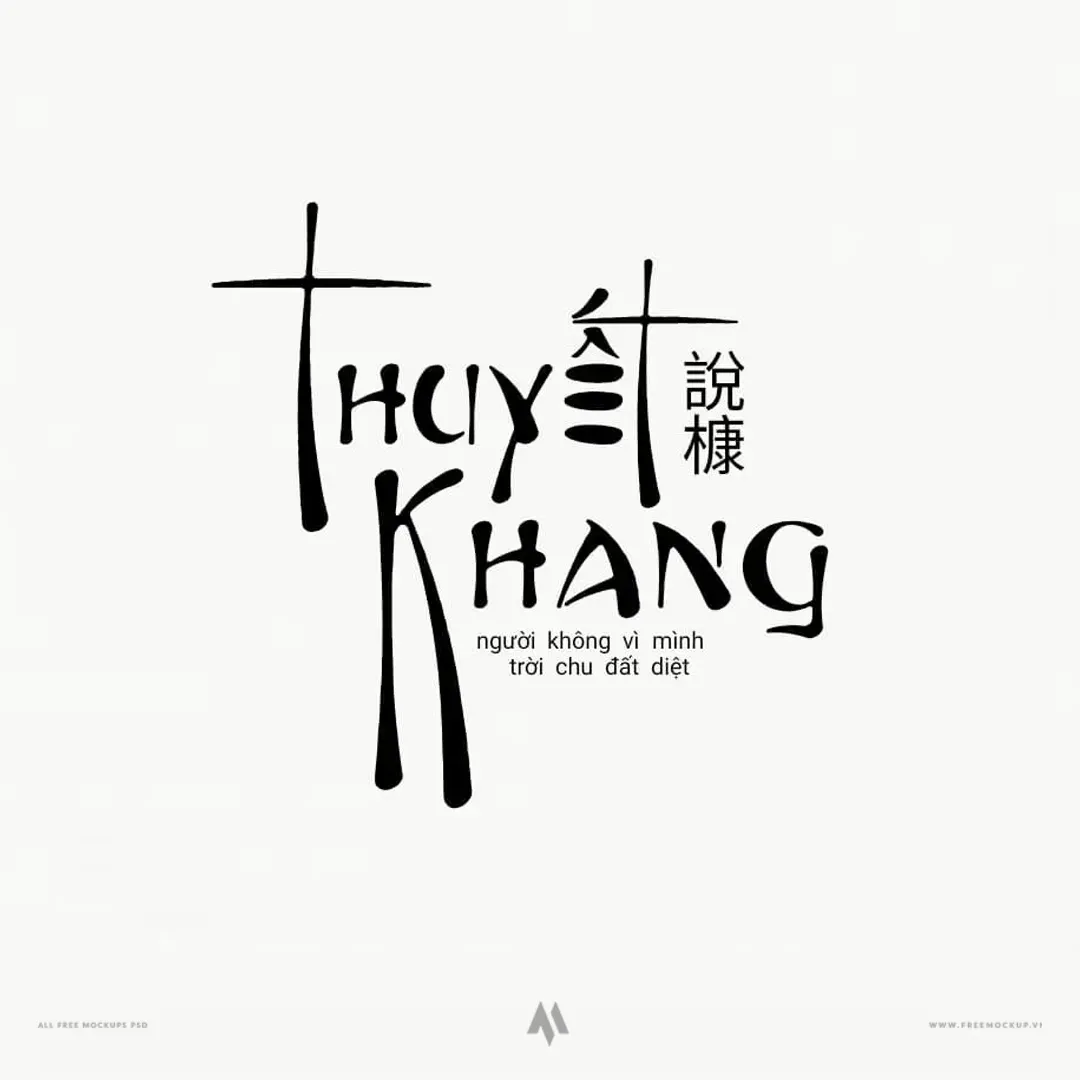
Font Fontasia Việt Hóa là bộ font chữ thư pháp (Calligraphy) ấn tượng được thiết kế bởi Walter Velez, mang đậm phong cách nghệ thuật cổ điển xen lẫn nét phóng khoáng, uyển chuyển. Toàn bộ hệ thống ký tự và dấu tiếng Việt đã được tinh chỉnh hoàn chỉnh, giúp các nhà thiết kế dễ dàng ứng dụng mà không lo lỗi font hiển thị.
Đặc điểm nổi bật
- Nét cọ thư pháp sắc sảo: Từng đường uốn lượn và độ đậm nhạt được cân chỉnh tỉ mỉ, tạo chiều sâu thị giác và cảm giác như được chấp bút thủ công.
- Chuẩn hóa tiếng Việt: Bộ dấu được đặt chuẩn tỉ lệ, tương thích mượt mà trên các phần mềm đồ họa phổ biến như Adobe Photoshop, Illustrator, InDesign hay Canva.
- Tạo điểm nhấn mạnh mẽ: Phù hợp làm tiêu đề chính nhờ tính thẩm mỹ cao và sự cuốn hút tự nhiên.
Ứng dụng tiêu biểu trong thiết kế
- Ấn phẩm xuất bản: Bìa sách, tiểu thuyết nghệ thuật, bìa tạp chí, thơ ca và ấn phẩm văn học.
- Quảng cáo & Truyền thông: Poster sự kiện, banner quảng bá, biểu ngữ, standee và hình ảnh viral trên mạng xã hội.
- Thiết kế thương hiệu: Logo mang hơi hướng vintage/retro, nhãn mác sản phẩm thủ công, thiệp mời và bao bì quà tặng cao cấp.